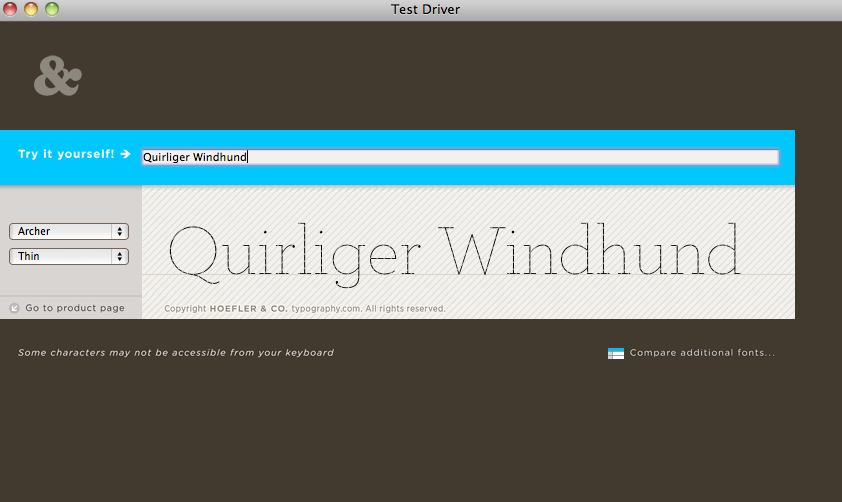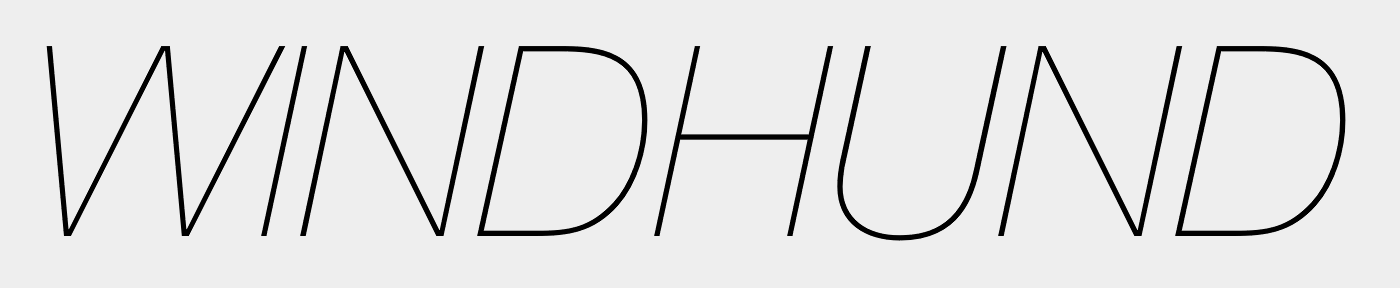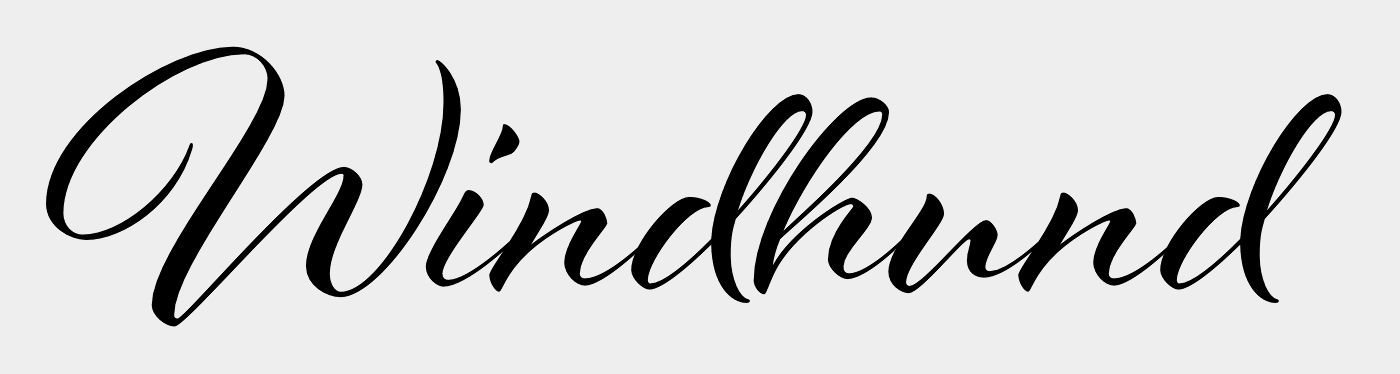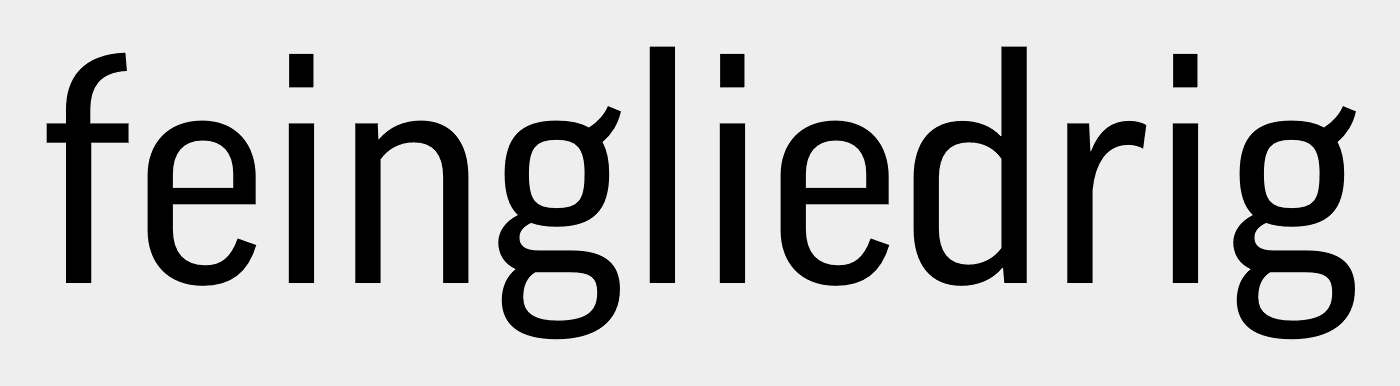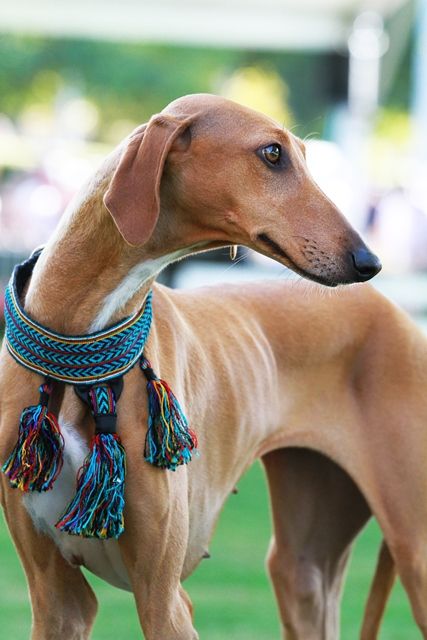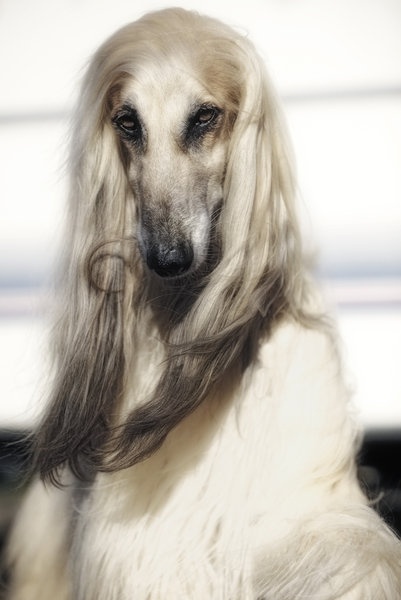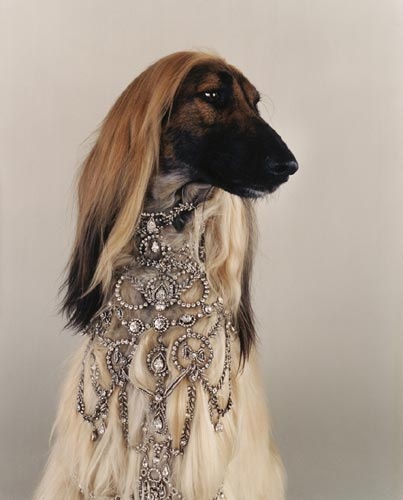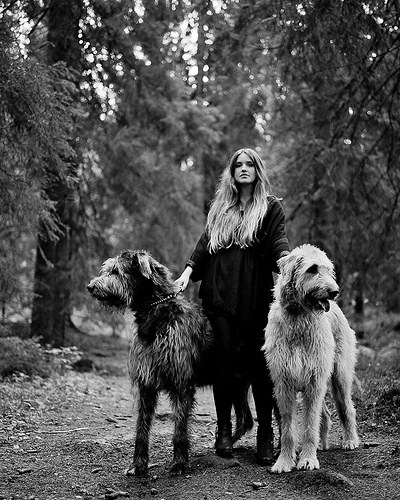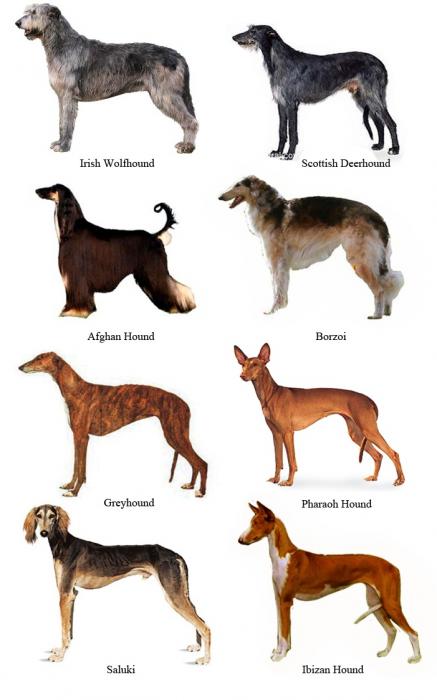
SCHRIFT passend thematik WINDHUND
ich suche eine schrift / familie, die der anmutung des windhundes entspricht.
hier einige adjektive, um diese rasse zu bechreiben.
— anatomische merkmale
- dünn schmal zerbrechlich feingliedrig muskolös erhaben majestätisch grazil ästhetisch anmutig elegant
- schnell quirlig fliegend windig stürmisch
— wesensmerkmale
- fröhlich eigensinnig stolz
- zäh, nervenstark, charakterfest
- erhaben ruhig
- stolzer individualist selbstständig
- aber auch zerbrechlich
im anhang findet ihr einige bilder, die die anmutung der schrift wiederspiegeln.
Es stellt sich aber auch erstmal die Frage: Was soll denn genau mit dieser Schrift gestaltet werden? Für ein Logo wäre ein Scriptfont denkbar, für Mengentexte natürlich nicht, beziehungsweise höchstens als Schrift für Headlines und Auszeichnungen.
Aber doch nicht so, eher ...
Sicher, sicher. An den Bussen stand es aber nun mal ziemlich fett. :-?
Dass das so war, stelle ich nicht in Frage – die Ultralight Italic war eher als neuer Impuls gedacht  :nicken:
wobei man das anhand der bilder die du gepostet hast eigentlich nicht verallgemeinern kann.
es gibt ja windhunde mit glattem fell, die schnell auf der rennbahn sind und dann gibt es diese modellhunde, da passt dann eher etwas graziles ...
oder halt diese afghanen, haarigen ...